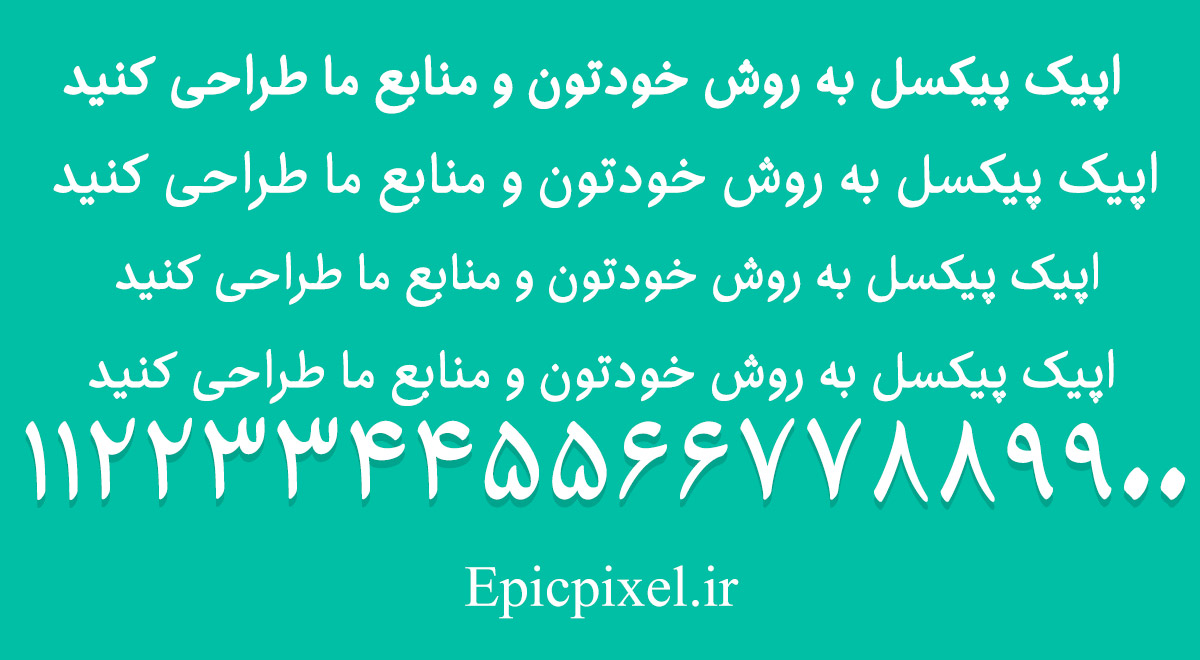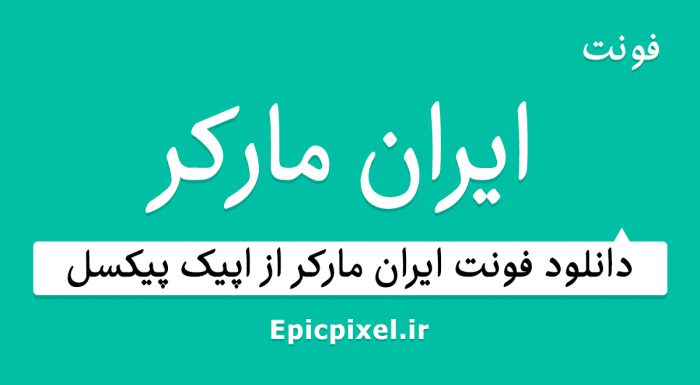
فونت ایران مارکر فارسی
فونت ایران مارکر چیست؟
فونت یا قلم یکی از عناصر اساسی در طراحی گرافیک، سایت، لوگو، بروشور، پوستر، کارت ویزیت و … است. فونت تاثیر بسزایی بر رسالت، هدف، شخصیت و حس مورد نظر طراح دارد. بنابراین، انتخاب فونت مناسب بسیار حائز اهمیت است.
فونت ایران مارکر یکی از فونتهای فارسی است که در سال ۱۳۹۹ توسط شرکت طراحی ایران تایپ طراحی و عرضه شده است. این فونت با الهام از خط نستعلیق و با استفاده از قلم مارکر خلق شده است. فونت ایران مارکر دارای ویژگیها و خصوصیات زیر است:
فونت ایران مارکر یک فونت بدون سرخط و پایینخط است که به آن فونت سنسسریف گفته میشود. این نوع فونتها معمولاً خوانایی بالاتری دارند و برای متون طولانی مناسبتر هستند.
فونت ایران مارکر یک فونت دستنوشته است که با قلم مارکر نوشته شده است. این نوع فونتها حس گرم، صمیمی، خلاق و شخصی به طراحی میدهند و برای متون خاطرات، داستان، شعر، تبلیغات و … مناسباند.
فونت ایران مارکر یک فونت چندزبانه است که علاوه بر پشتیبانی از زبان فارسی، از زبانهای عربی، کُردی، اُردُو، پشتو، تاتی، تالشی، لُری، بلوچی، آذربایجانی و … نیز پشتیبانی میکند.
فونت ایران مارکر با توجه به ویژگیهای بالا، یک فونت منحصر به فرد، جذاب و کاربردی است که میتوانید در طراحیهای خود از آن بهره ببرید. این فونت برای نمایش محتوای هنری، خلاق، شخصی و عاطفی مناسب است. همچنین، با تغییر سبک، رنگ و اندازه فونت، میتوانید حالات و رسالات مختلف را با آن ابراز کنید.
چگونه فونت ایران مارکر را بهینهسازی کنیم؟
فونت ایران مارکر یک فونت با کیفیت و زیبا است که میتوانید با تنظیمات و پارامترهای مختلف آن را بهینهسازی کنید. بعضی از تنظیمات و پارامترهای مهم در استفاده از فونت ایران مارکر عبارتاند از:
فونتهای سازگار با فونت ایران مارکر
مثالها و نمونههای کاربردی از فونت ایران مارکر
فونت ایران مارکر برای طراحی گرافیک
فونت ایران مارکر برای طراحی سایت
فونت ایران مارکر برای طراحی لوگو
فونت ایران مارکر برای نگارش و ویرایش متون
فونت ایران مارکر برای نوشتن شعر و داستان
فونت ایران مارکر برای نمایش محتوای هنری و خلاق
فونت ایران مارکر برای نمایش محتوای شخصی و عاطفی
فونت ایران مارکر چه سالی طراحی شده است؟
فونت ایران مارکر چه نوع فونتی است؟
فونت ایران مارکر چه ویژگیهایی دارد؟